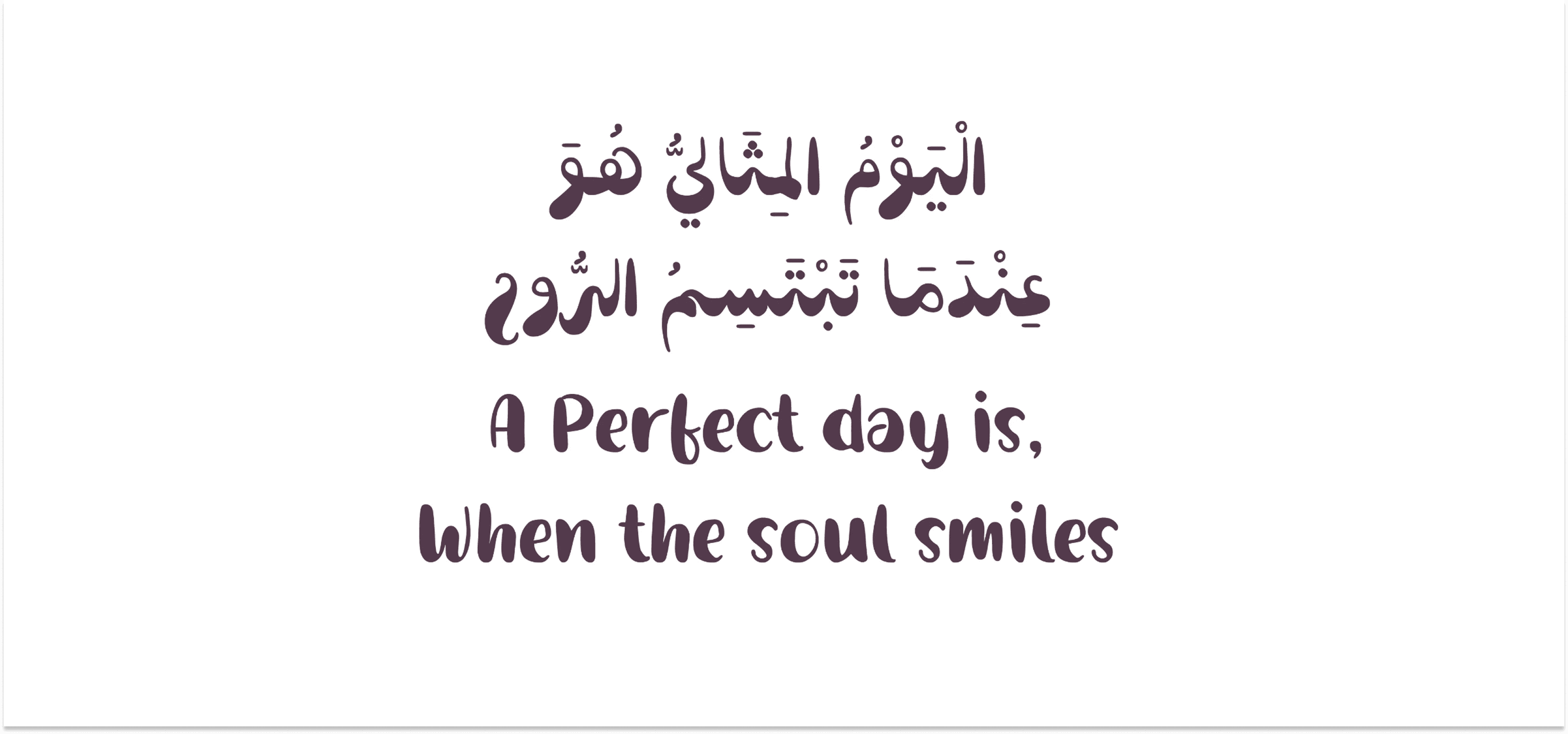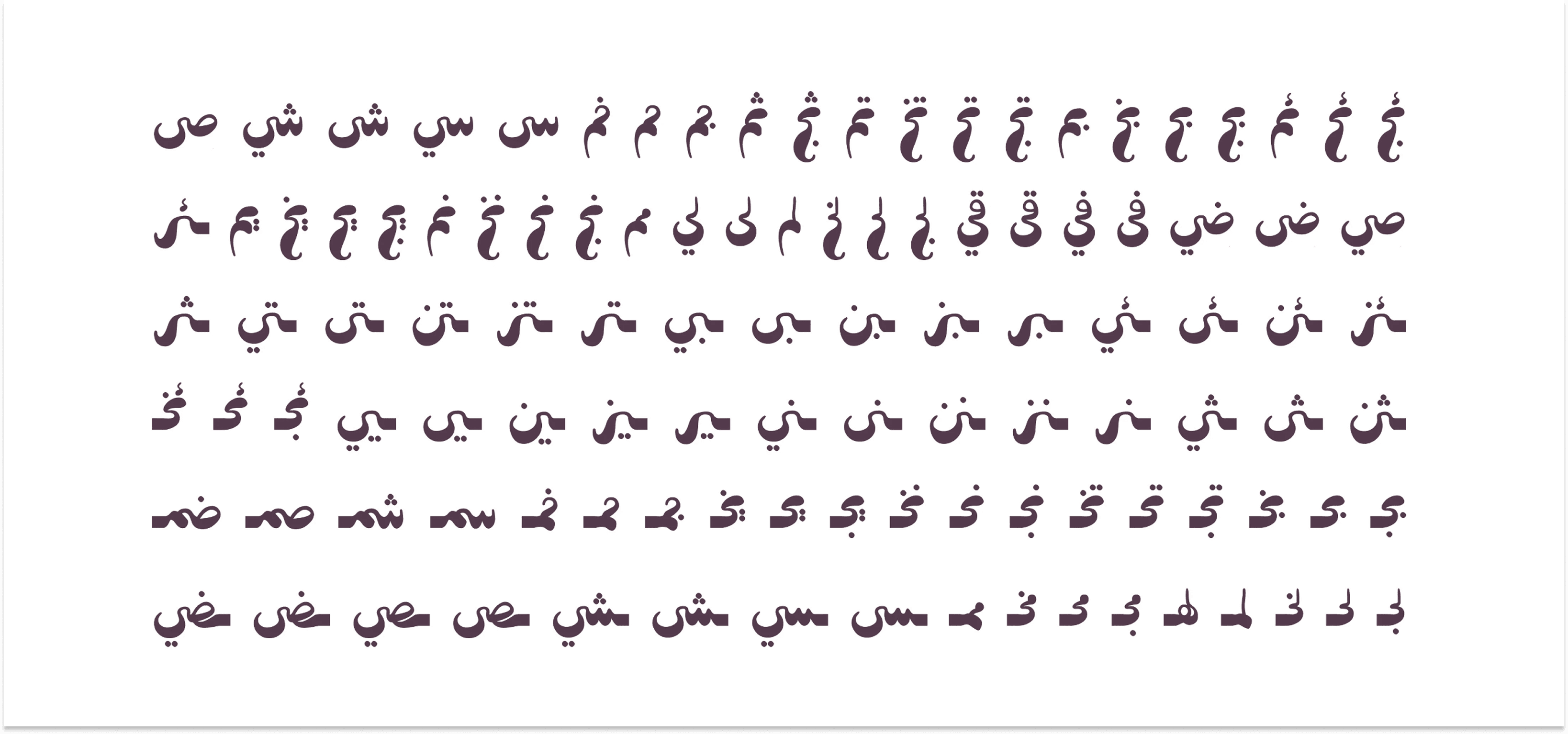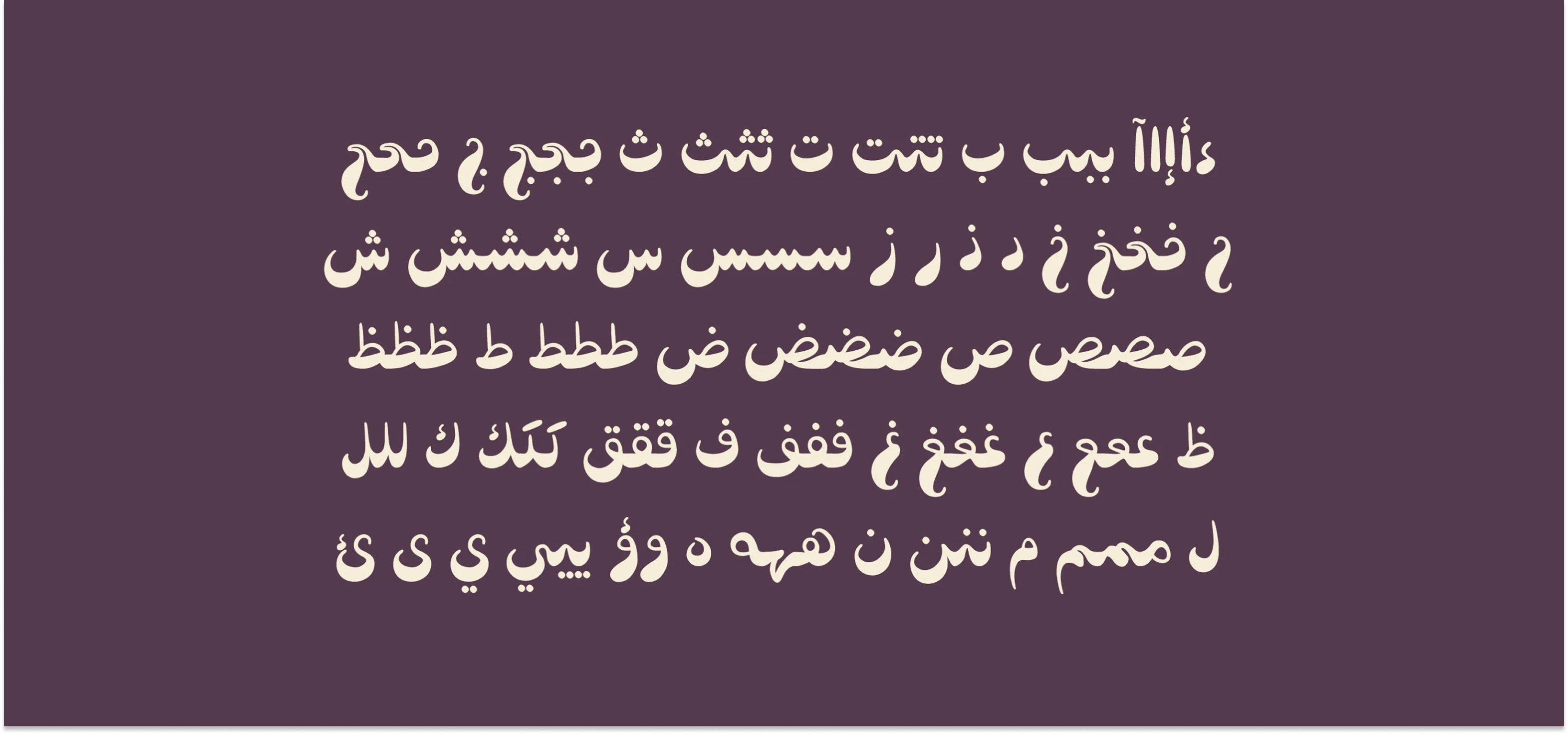
Qunqulez (2020) هو خط يدوي عربي/لاتيني بأسلوب فرشاة الرسم (Brush Font) يتميز بطابع عفوي وحيوي، ما يجعله مثاليًا لتصميم الشعارات، العناوين، الملصقات، الإعلانات، وتغليف المنتجات.
الخصائص:
يدعم اللغتين العربية والإنجليزية
يتضمن ربطات (Ligatures) عربية، وحروف لاتينية كبيرة وصغيرة
يشمل الأرقام وعلامات الترقيم
Qunqulez يمنح تصاميمك طابعًا فنيًا وملفتًا، يجمع بين الجرأة اليدوية والبنية المتوازنة.